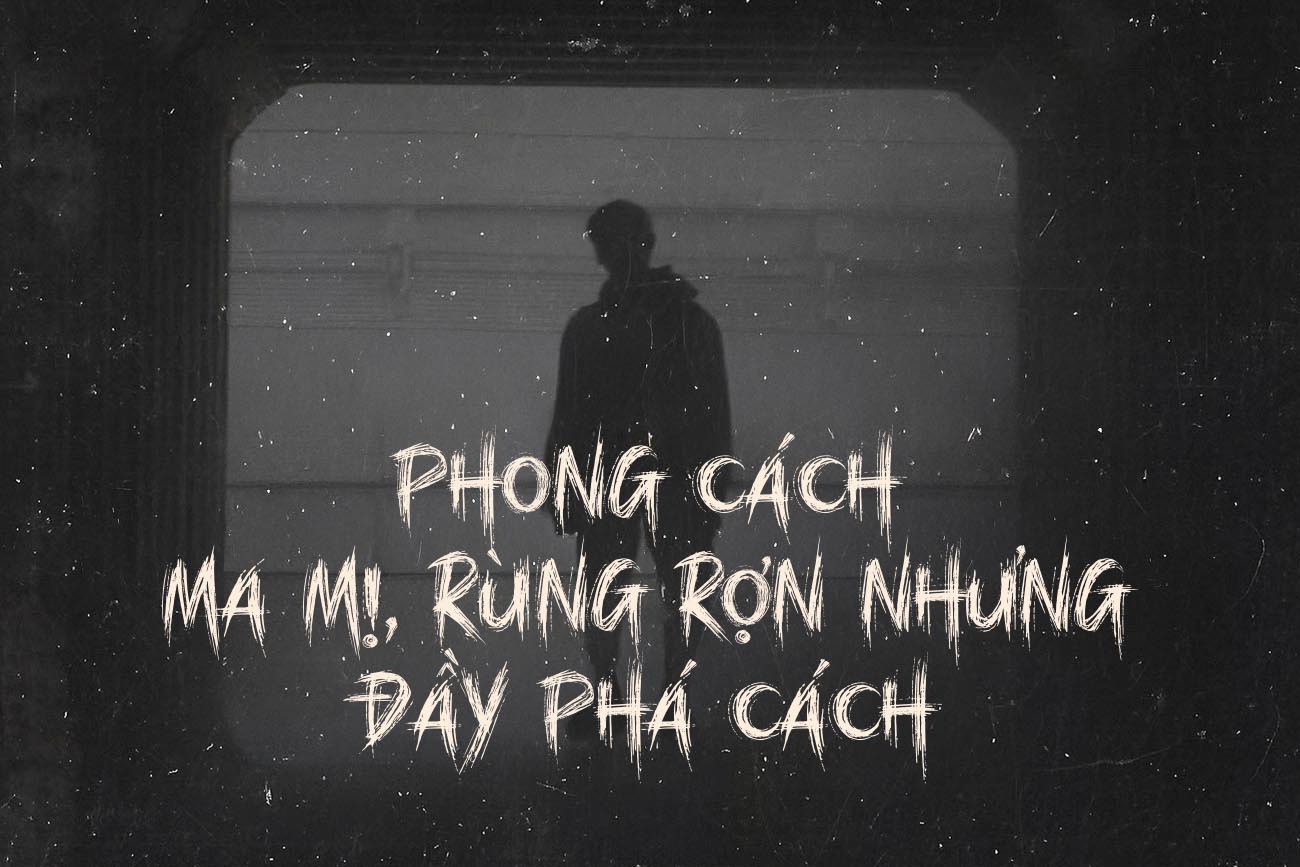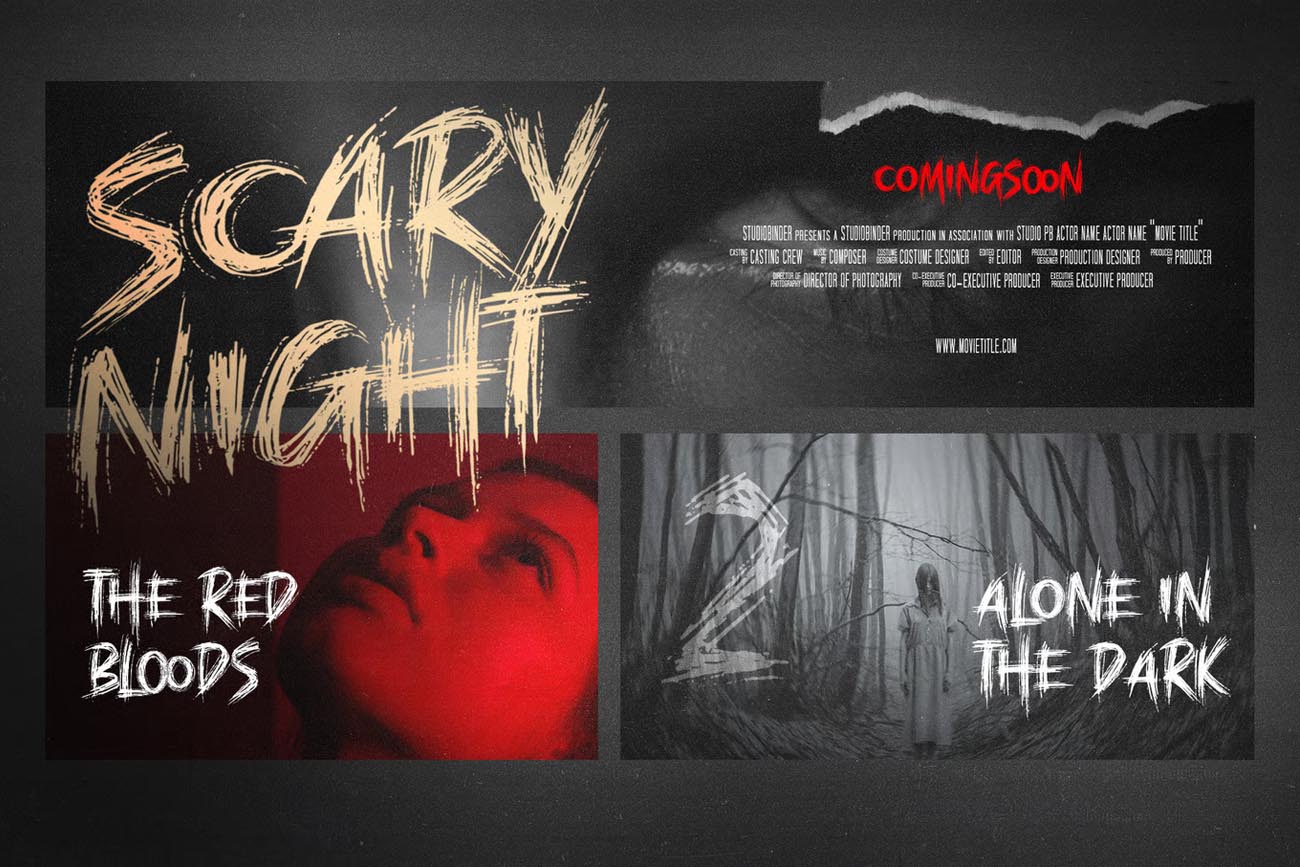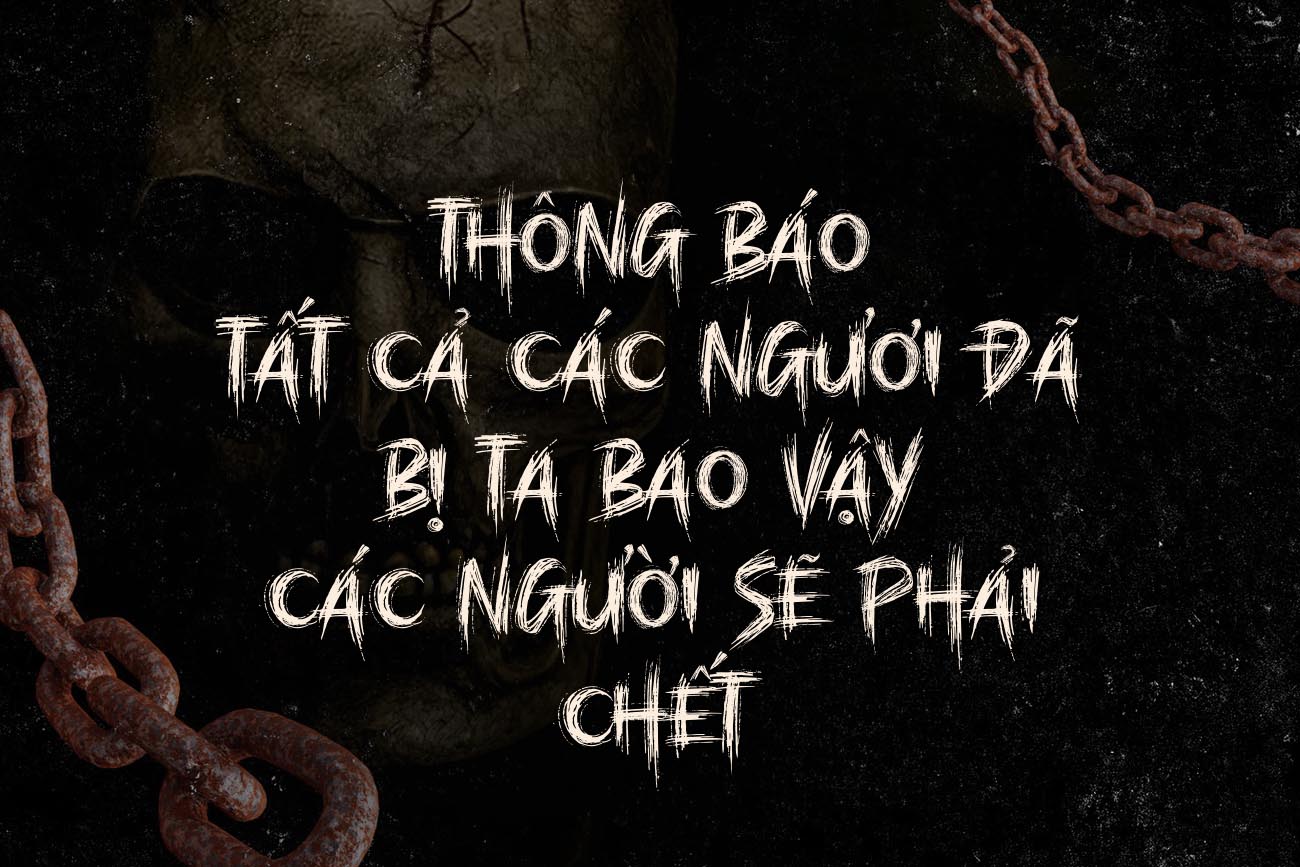
Font chữ kinh dị phong cách Brush đầy ám ảnh - TH Marching Việt hóa
Trong thế giới thiết kế đồ họa, đặc biệt là khi thực hiện các dự án mang màu sắc u tối hay huyền bí, việc lựa chọn Typography đóng vai trò quyết định đến cảm xúc của người xem. Nếu bạn đang tìm kiếm một font chữ kinh dị sở hữu nét vẽ tay mạnh mẽ và đầy ma mị, TH Marching Brush chính là sự lựa chọn hoàn hảo dành cho bạn.
Nguồn gốc và phong cách thiết kế
TH Marching Brush được Việt hóa từ phông chữ gốc Marching Brush, một sáng tạo độc đáo của tác giả Subec (hiện đang được phát hành trên Envato Elements). Khác với những kiểu chữ Serif cứng nhắc, bộ phông này mang đậm phong cách Rough Brush (cọ xước).
Các đường nét của chữ được mô phỏng như những vệt mực khô, tạo cảm giác gấp gáp, hoang dại và có phần rùng rợn. Chính sự "bừa bộn có chủ đích" này đã giúp Marching Brush trở thành một font chữ kinh dị xuất sắc, dễ dàng gây ấn tượng thị giác mạnh ngay từ cái nhìn đầu tiên.
Tại sao nên sử dụng phiên bản Việt hóa bởi Team TH?
Mặc dù bản gốc của Subec đã rất ấn tượng, nhưng rào cản lớn nhất đối với Designer Việt Nam chính là hệ thống dấu tiếng Việt. Hiểu được điều này, Team TH đã thực hiện công đoạn Việt hóa một cách tỉ mỉ và tinh tế.
Phiên bản TH Marching Brush không chỉ đơn thuần là thêm dấu. Các dấu mũ, dấu thanh được Team TH cân chỉnh kỹ lưỡng về khoảng cách (kerning) và vị trí, đảm bảo sự cân đối tổng thể mà không làm mất đi "chất" hoang dại của bản gốc. Nhờ đó, bạn có thể thoải mái sáng tạo các nội dung tiếng Việt mà không lo gặp lỗi hiển thị hay bố cục rời rạc.
Ứng dụng thực tế
Với đặc tính là một font chữ kinh dị nổi bật, TH Marching Brush cực kỳ phù hợp cho:
- Poster phim kinh dị, trinh thám hoặc phim hành động giật gân.
- Bìa sách, truyện tranh chủ đề Halloween hoặc tâm linh.
- Thumbnail Youtube cho các kênh kể chuyện ma.
- Thiết kế giao diện Game (UI) mang phong cách sinh tồn.
Lời kết
TH Marching Brush là minh chứng cho thấy một phông chữ tốt có thể nâng tầm thiết kế của bạn như thế nào. Xin cảm ơn tác giả Subec vì bản gốc tuyệt vời và Team TH đã mang đến một bản Việt hóa chất lượng cho cộng đồng. Hy vọng bộ font chữ kinh dị này sẽ là trợ thủ đắc lực trong các dự án sắp tới của bạn.